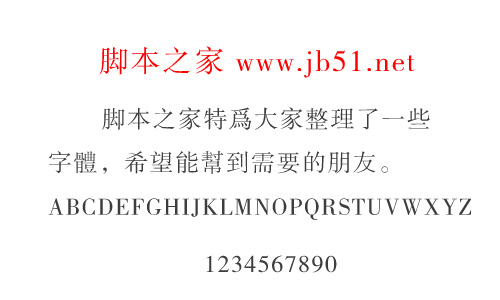
方正新書宋繁體字體是方正字體庫中的一種字體,方正新書宋是原方正書宋的優(yōu)化版。其設(shè)計(jì)從正文字體的科學(xué)性、人文性和審美性角度出發(fā),旨在提高字體的適讀性,改善正文字體的應(yīng)用環(huán)境。方正新書宋字形更趨向方正寬博,中宮略放松,重心稍降低,字面大小勻稱。成段后的文本行氣貫通,灰度均勻,輪廓整齊,閱讀效果更為舒適和流暢。特別適用于各類雜志和書籍的正文排版。喜歡的朋友們可以前來下載使用。